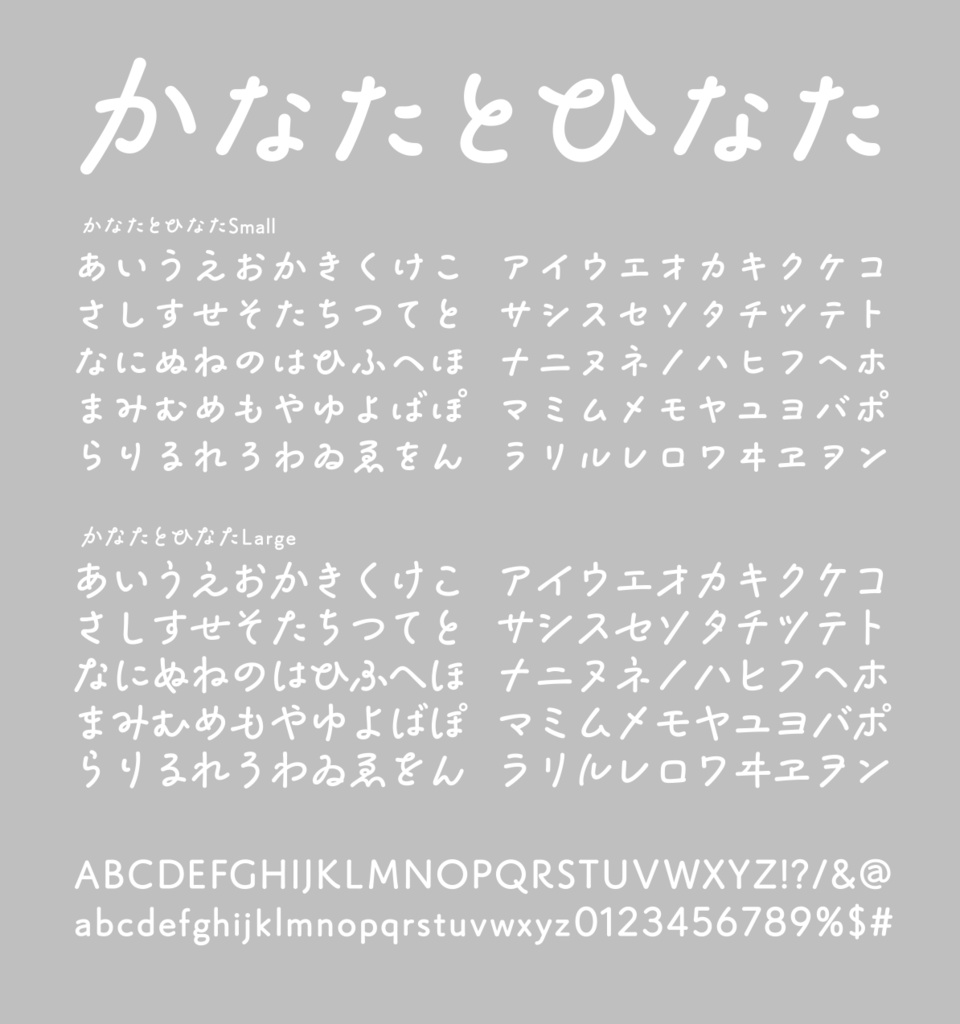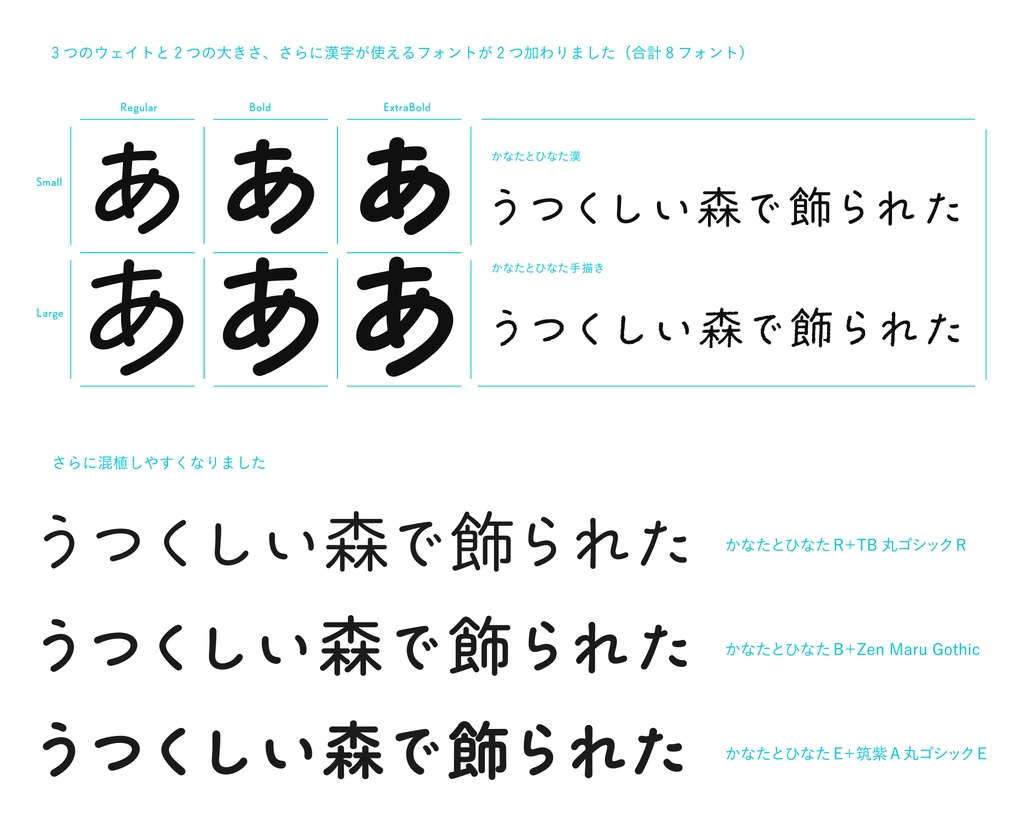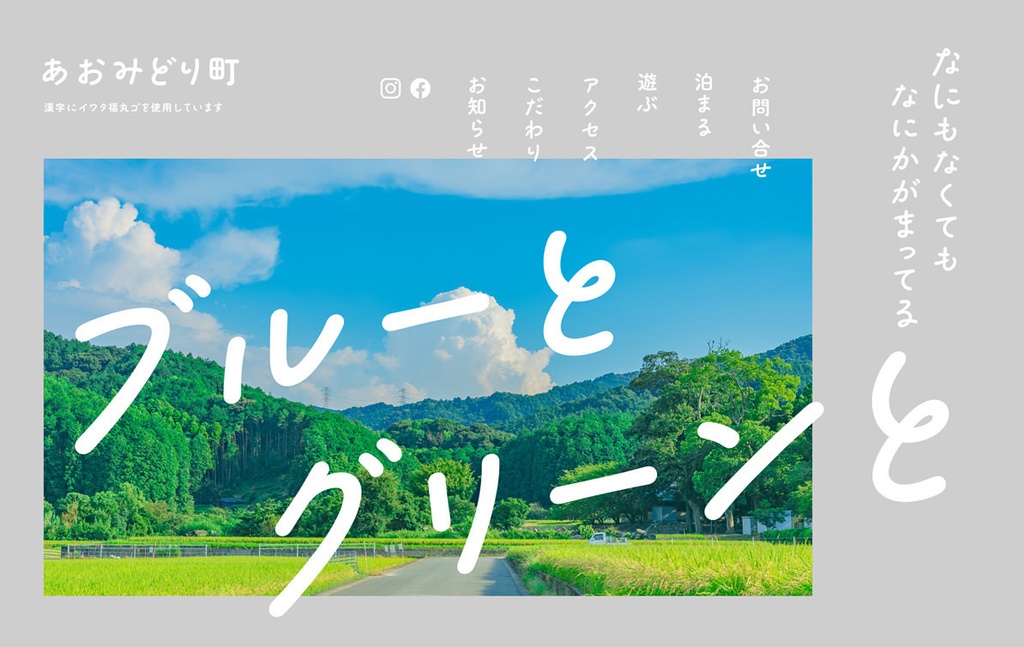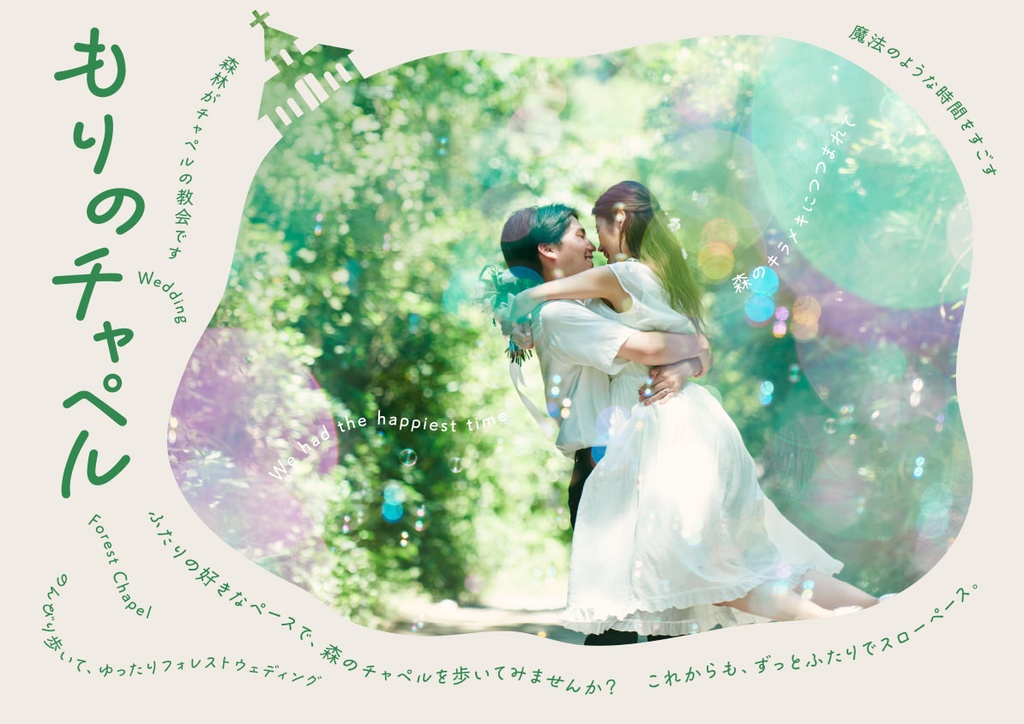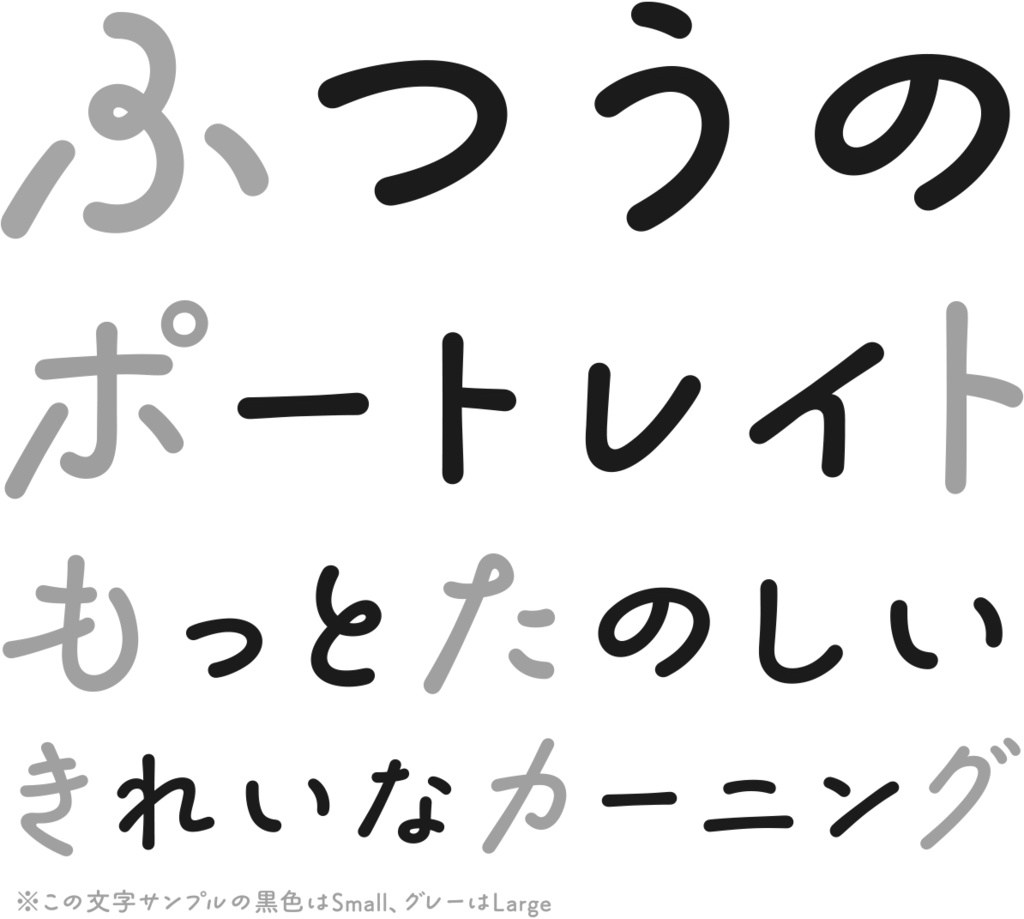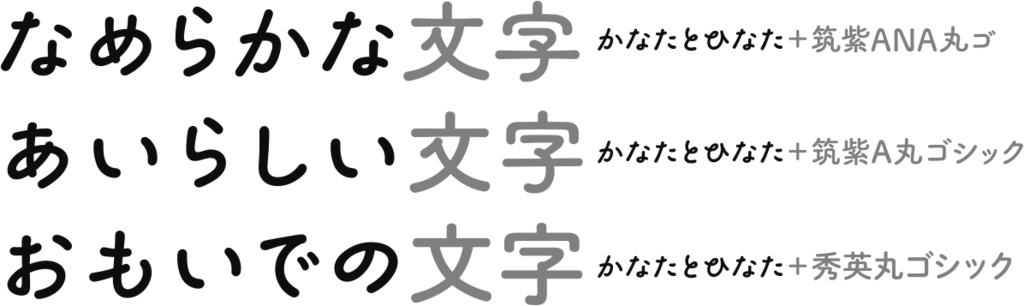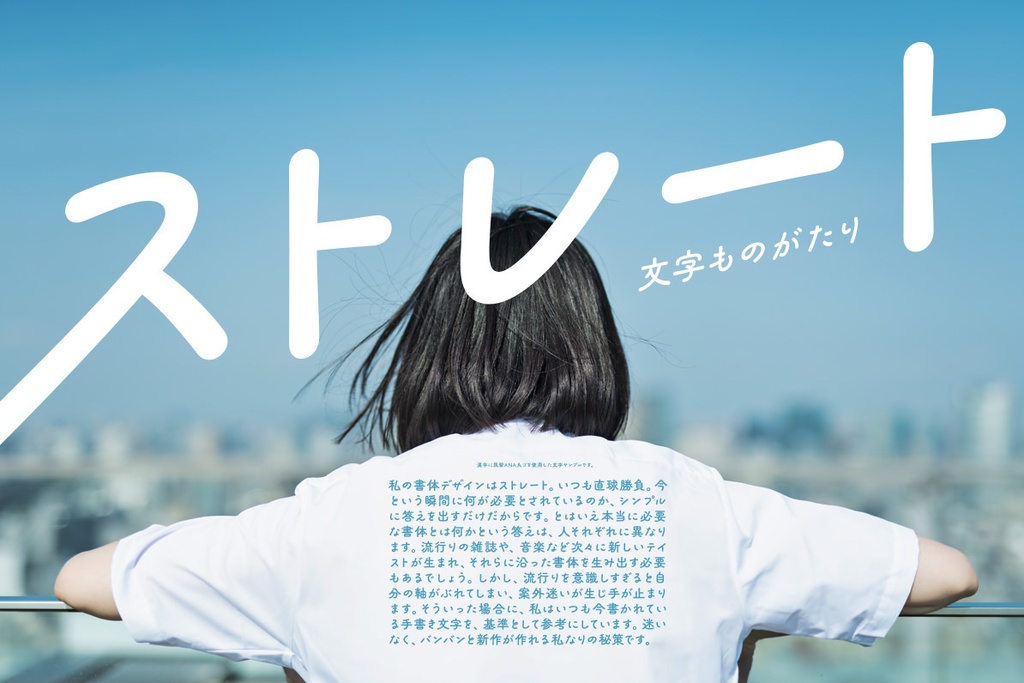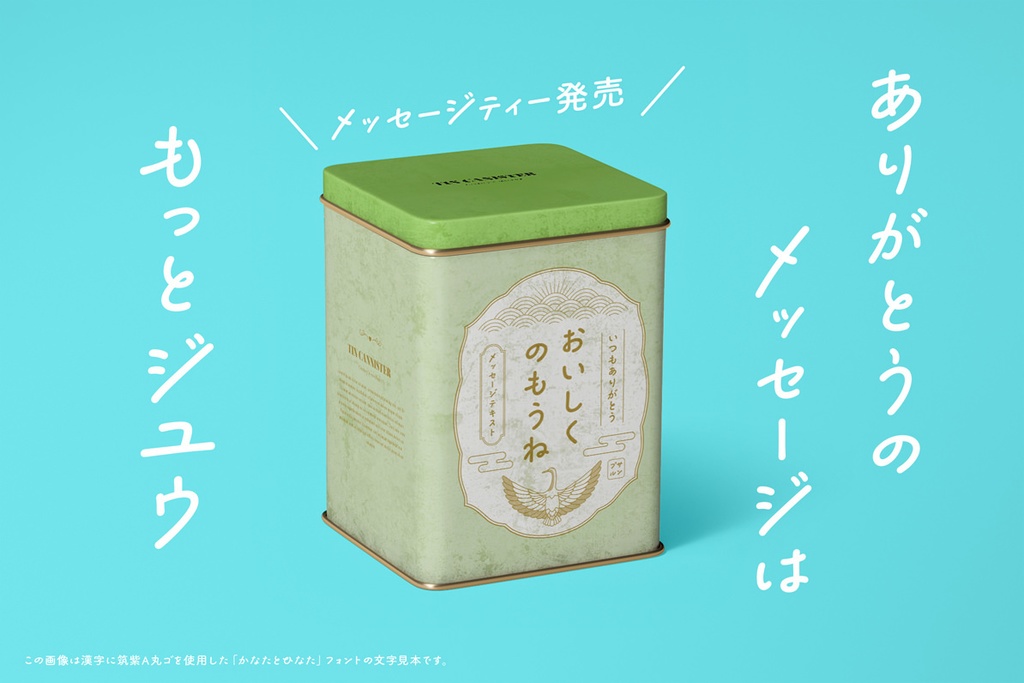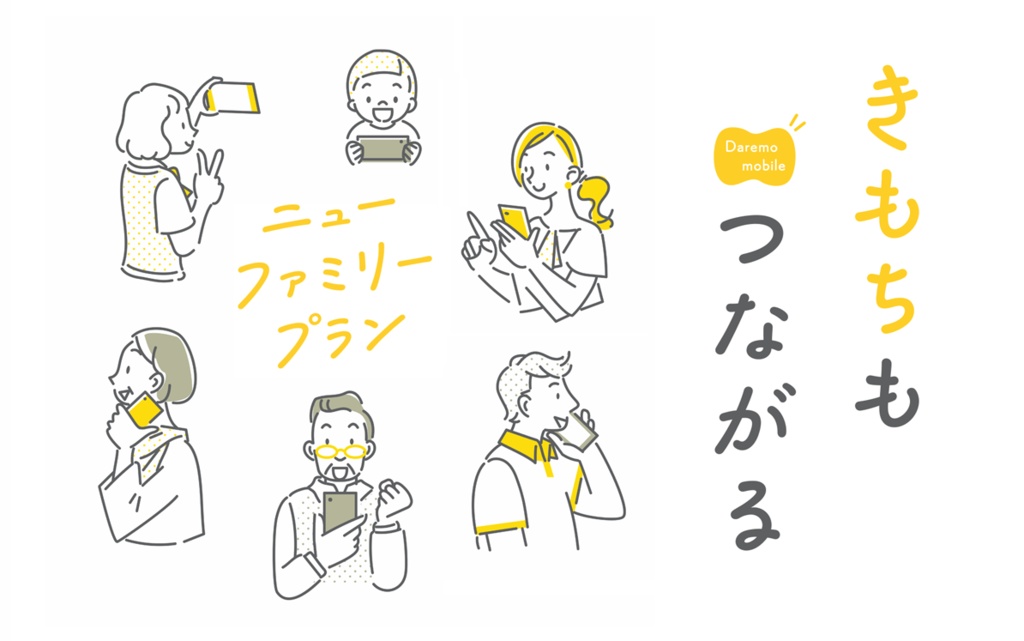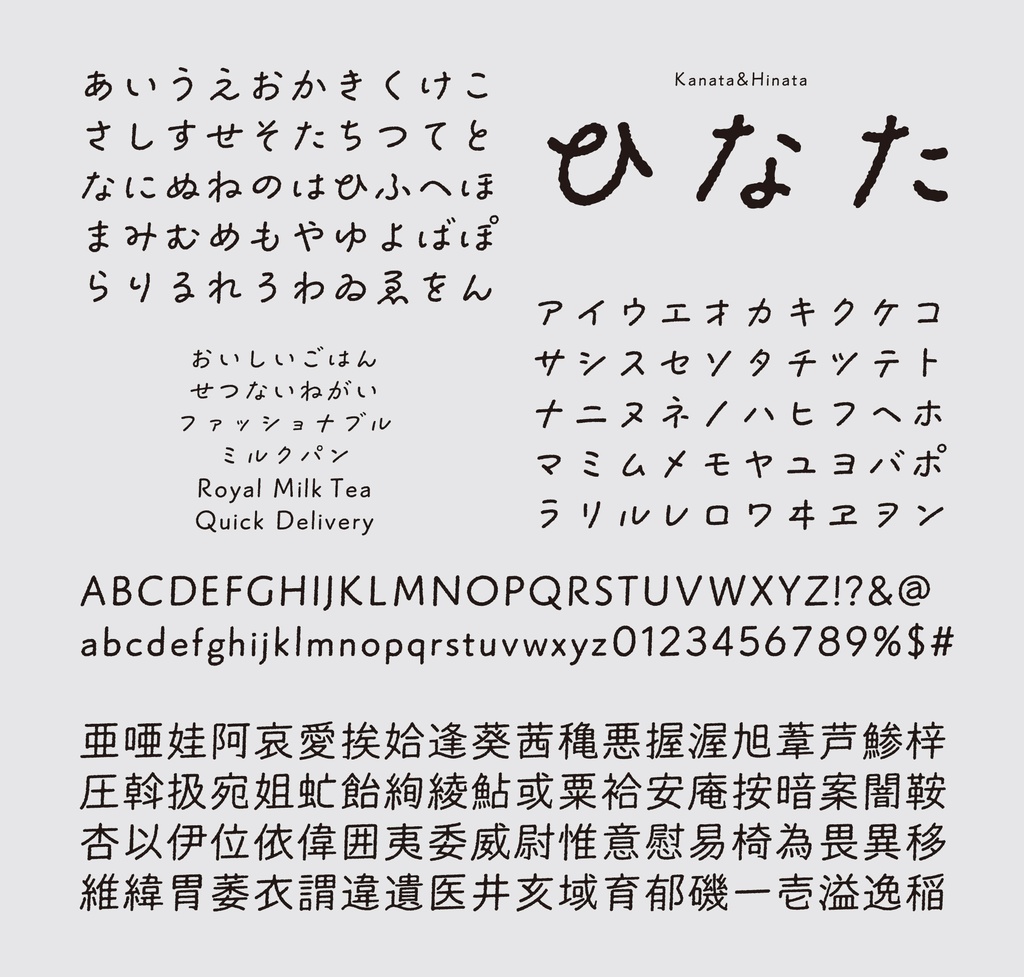
【期間限定で半額】6980円→3490円。11月の一部商品の値上げのお詫びとして、10月26日まで割引きを実施いたします。 温かみ・優しさ・手作り感のあるシーンにベストマッチする手描き風の丸ゴシック体。ロゴデザイン、写真への文字入れ、漫画への使用などで特に大活躍。R・B・Eの3種類の太さに加えて、大きさの違うSmallとLarge、漢字が使える2つのフォントの合計8フォント収録。 ■動作環境 Mac:システム/OS X対応(10.x)最新のOS X Windows:OS/日本語版Windows2000、XP、VISTA、Windows7〜11以降 フォント形式:OpenTypeフォント ※Adobeイラストレーター、フォトショップはもちろんのことWindows用ワード・エクセル等でもご使用になれます。 1商品(1ライセンス)につき1ユーザー1PCのみがご利用いただけます。複数人で使用する場合は人数分をご購入ください。 ■収録文字数について 「かなたとひなた」R・B・Eの3ウェイト 収録文字数360字 ※収録文字はアルファベット、ひらがな、カタカナ、約物の一部。 「かなたとひなた漢-R」「かなたとひなた手描き-R」 収録文字数4,600文字(第一水準2965文字+第二水準475文字+ひらがな、カタカナ、約物、記号、アルファベット等1160文字) 合計8フォント収録 ■安心して使えるロイヤリティフリーの書体 あらゆる商用・デザイン用途(印刷物・ゲーム・アプリ・映像・動画・ロゴ・同人作品)に使用できる、商用申請の必要のないロイヤリティフリーの書体になります。文字の加工・変形も可能です。ご安心ください。 ■デザインコンセプト ラフな手描きの勢いを感じさせつつも・文章としての読みやすさを考えて作られた書体デザイン。やさしい雰囲気とかっこいい勢いの両方の要素があり中性的な印象になっています。 ■2種類のサイズのフォント 丸ゴシック体で一番小さいサイズのSmallと、伸びやかで大きなLargeの2つのセットです。SmallとLargeの2種類を組み合わせると、より手描きらしい抑揚のある表現が可能です。その際はSmallをまず文章全体に使用し、所々をLargeに変更するのがオススメです。 ■OpenType機能 詰め組み機能 ペアカーニング(仮名・プロポーショナル欧文) 字形切り替え機能(1つの文字で異なる字形を用意しています) デザインの幅をグッと広げる、手描き風の丸ゴシック体です。